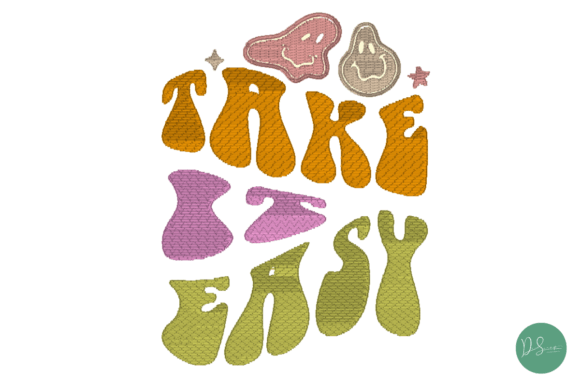
Take It Easy
قد يكون العثور على عناصر التصميم المناسبة أمرًا صعبًا، ولكن Take It Easy يقدم مجموعة استثنائية ترتقي بعملك على الفور.
تم تصميمه بدقة، ويوفر Take It Easy متجهات نظيفة وطباعة سلسة وترخيصًا تجاريًا لراحة بالك.
سواء كنت تقوم بإنشاء منتجات الطباعة عند الطلب أو دعوات الزفاف أو رسومات وسائل التواصل الاجتماعي، فإن Take It Easy هو الخيار المثالي.